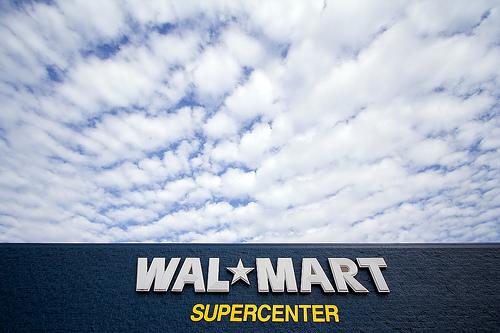
neues Walmart-Logo
looks like a sphincter?
Walmart; assholes.
HAHAHA!
Yo, das dürfte die Myriad sein.
Sieht schön billich aus, passt doch :wink:
Billig ja, aber das wesentlich eigenständigere Logo, dass sich bereits ins Hirn vom hunderten Millionen Menschen gebrannt hatte, wurde wiedermal völlig unmotiviert aufgegeben.
ich erinnere mich schwach ... aber ich glaube die hatten damals auch ein
W in american typewriter also signet.
das jetzige logo sieht aus als machen sie auf enmal auf öko oder so.
frisch, fetzig und neu. das alte war doch eines der amerikanischsten logos
überhaupt. da hätte man ruhig mal etwas patriotismus zeigen können.
jetzt siehts aus wie eine kleine französische kette. vielleicht will man sich ja
reinwaschen ... von ss-shirts, bush und co.